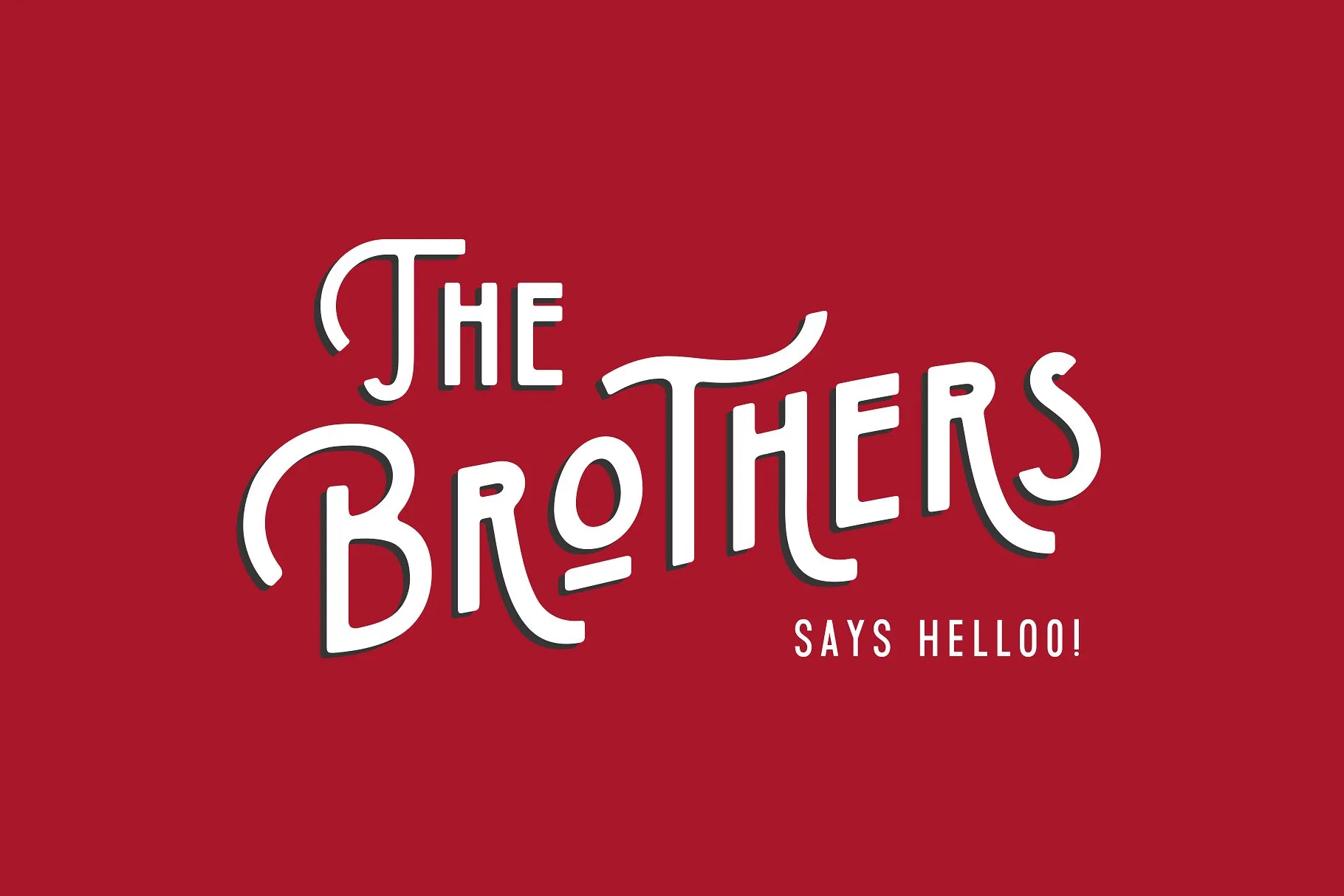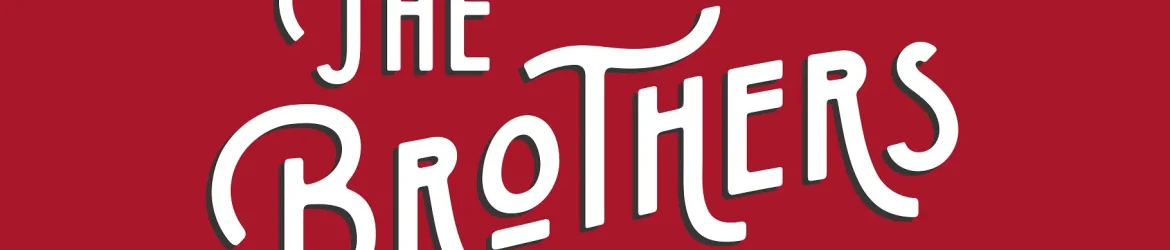
Introduzimos a Clethons Djoice Typeface fonte. Ela foi criada pelo designer cob e é uma fonte premium disponível no site Creativemarket. Agora, por uma breve promoção, ela está gratuita para download hoje. Esta fonte Vintage é perfeita para uso em tipografia, letraing, logotipia e muito mais. +200 contagens de caracteres suaves foram adicionadas, incluindo os recursos OpenType que trazem uma variedade interessante de estilos como Elegant Design, Modern, Vintage e Retro. Esta fonte é perfeita para designers que buscam algo elegante e versátil, capaz de dar um toque vintage a qualquer design moderno ou moderno em estilo retro.